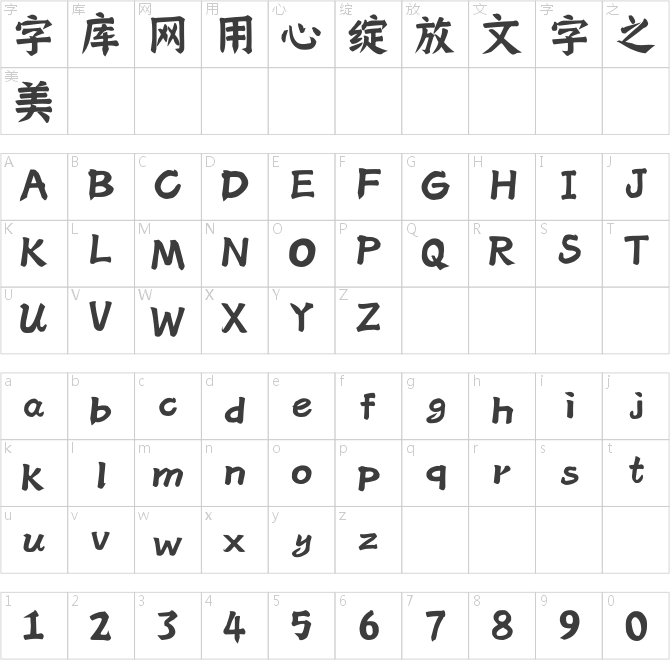
逐浪粗顏楷 詳情頁
字體名稱: 逐浪粗顏楷
作者版權: 逐浪字庫
逐浪粗顏楷
逐浪粗顏楷介紹
撇畫如柳葉小刀出尖鋒、略拉長
橫加粗口形露聳肩
上點加粗豎畫下方當為粗垂針或大刀形
豎還可以帶勾
字形入筆追求傳統,多采用傳統的藏鋒左切結構(避免右傾刀鋒結構)
筋骨豐滿遒勁有力
內斂如弓拉滿弦
是不可多得的現代經典顏體字庫。